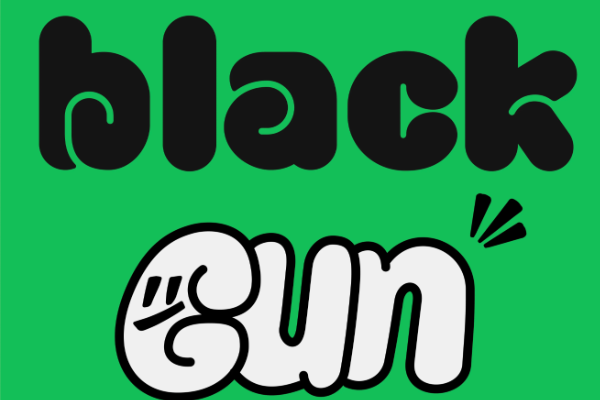
xiaoheigungunti-Bold
xiaoheigungunti-Bold是一款充满趣味的英文创意字体,主打卡通可爱风格,以超粗字重和圆润笔触为核心设计亮点。字体采用方正结构,重心居中且中宫宽博,超粗字重搭配均匀的笔画分布,展现出浑厚饱满的视觉效果。其笔画设计以圆润线条为主,末端多为圆头形态,并点缀着俏皮的装饰性小圆弧,巧妙运用圆滚动痕迹形成独特正负形,融合几何图形的运动感,赋予文字活泼生命力。连笔设计增强了字符间的连贯性,让整体排版更具流动美感。作为免费商用字体,xiaoheigungunti-Bold在标题设计、LOGO创作等场景中表现卓越,能迅速抓住视觉焦点,传递轻松愉悦的品牌调性。尽管字符集较小,但其独特的艺术表现力足以满足各类创意设计需求,是设计师打造趣味视觉作品的理想选择。